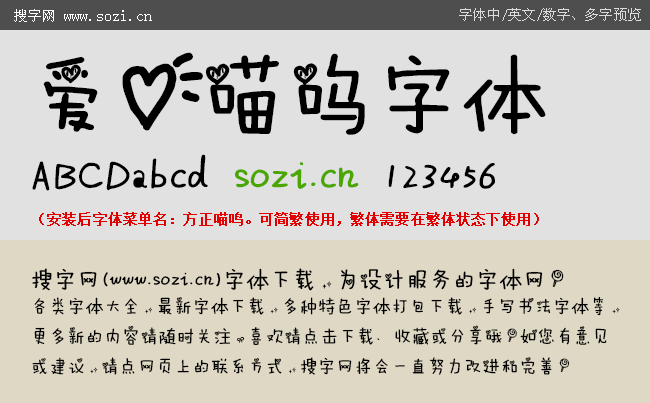
愛(ài)心喵嗚字體(FZMM)
搜字網(wǎng)給大家提供一款很卡通的手機(jī)中文字體下載。修改者將它命名為心心喵嗚中文字體,這款手機(jī)字體是以方正喵嗚體為原形,字體的一些筆畫替換成了非常有趣的卡通心形圖案,方正喵嗚體是少女漫畫家喵嗚聯(lián)手方正出品的一款手寫涂鴉字體,字形活潑、可愛(ài)、隨意,給人一種無(wú)憂無(wú)慮毫無(wú)約束的自由之感。特別適合喜歡手機(jī)字體個(gè)性一些的朋友在手機(jī)上安裝使用。